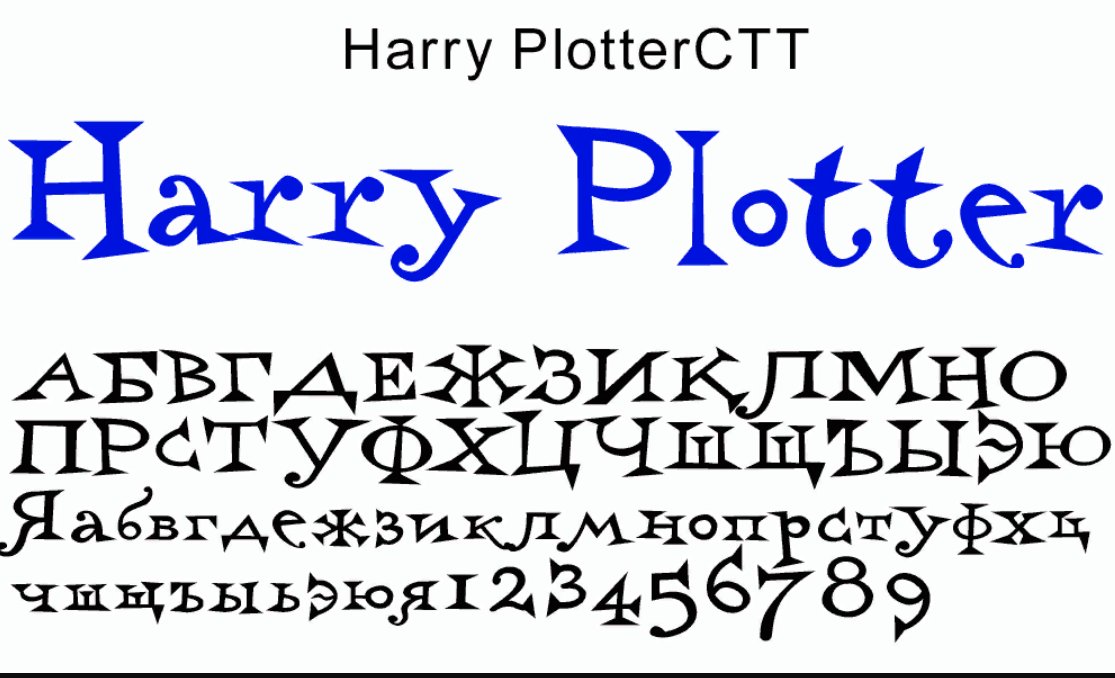
В современных реалиях почти что каждому приходилось хоть раз иметь дело с программами, рассчитанными на работу с графикой. Наверное, многие пользовались не только возможностями ретуширования и рисования в Adobe Photoshop, но и текстовыми инструментами. А между тем, правильное сочетание текста и красивой картинки дают некую визуализацию, которой активно пользуются в рекламе.
Правильное формирование текстовых символов вместе с визуальными эффектами насыщают изображение, и не перегружают смысл написанного. Новички, которые начинают осваивать приложение, задумываются, как загрузить шрифты в «Фотошоп». Хоть внутри программы и имеется определенный базовый набор шрифтов, все равно на практике требуются необычные и интересные начертания, которые будут завлекать читателя.
Прежде тем, как загрузить шрифты в «Фотошоп», необходимо понимать, что не все типы начертаний способны поддерживать кириллицу. Для создания шрифтов чаще всего используется латиница. - Третий способ помогает решить проблему с использованием программ-помощников. Они являются менеджерами шрифтов и облегчают работу с их установкой, управлением.
- Папку Fonts возможно найти и напрямую. Необходимо лишь пройти данный путь: C:WindowsFonts
Чтобы установить нужный пользователю шрифт, необходимо скопировать или перенести соответствующий файл в данную папку.
Добавление шрифтов в Adobe Photoshop
Если вы остановились на том методе, где файл со шрифтом добавляют в «Фотошоп» напрямую, то сначала нужно выяснить, какая папка отвечает за шрифты в программе. По умолчанию папка, где должны хранится файлы находится в системной папке Adobe Photoshop. Установка шрифтов производится путем добавления файлов в эту папку. После этого необходимо выйти из программы (если она была включена) и заново войти. Новый шрифт появится в списке доступных шрифтов сразу же.
Сторонние программы
Если пользователь довольно часто изменяет шрифты в «Фотошопе», удобным сервисом для него могут послужить некоторые приложения-помощники. Они способны автоматически добавлять, изменять и деактивировать шрифты различных форматов. Это может оказаться полезным для тех, кто использует несколько текстовых редакторов. Приложения не создают сильной нагрузки на операционную систему и не влияют на работу текстовых и графических редакторов.
Ниже представлен перечень менеджер-программ:
- Adobe Type Manager – удобное приложение, которое обладает необходимым функционалом для работы с текстовыми редакторами и шрифтами.
- Font Expert – одна из доступных и простых программ для использования.
Mexe
Mexe — еще один из этих удивительно сильных шрифтов. Он был разработан для конкретных заголовков, для комиксов и содержащих кириллицу.
Espacio Novo
Uni Sans
Uni Sans — еще один из этих классных стилей шрифтов для Photoshop или Illustrator, и вы можете использовать его для создания классных дизайнов шрифтов.
Ось
Авентура
Монтсеррат
Часто сравнивают с Proxima Nova за его очаровательную полезность. Montserrat — уникальный шрифт, любимый многими веб-дизайнерами и дизайнерами пользовательского интерфейса.
Рунд-Гротеск